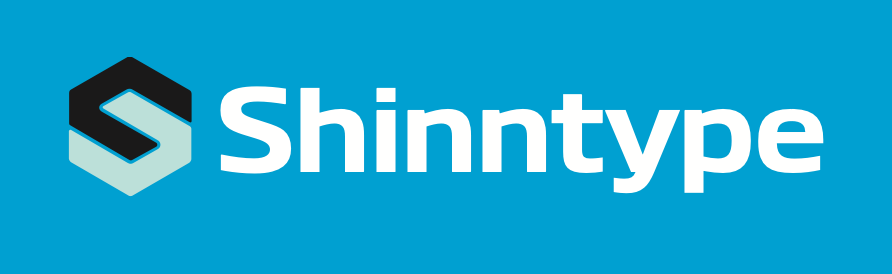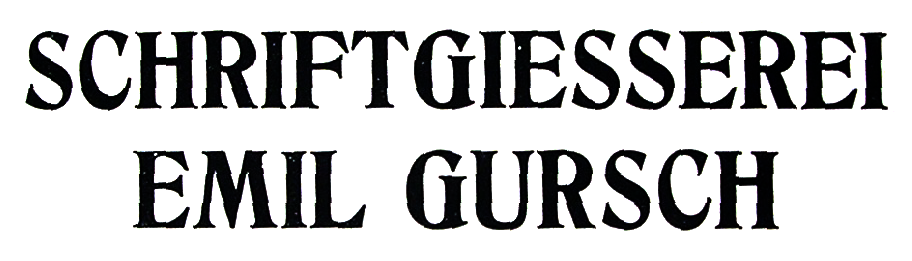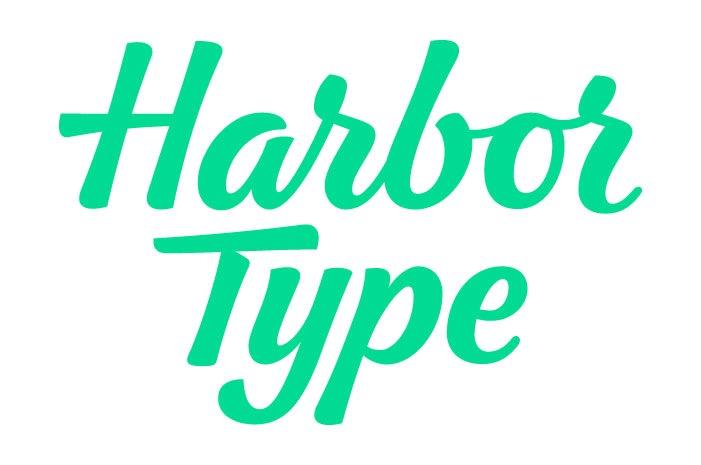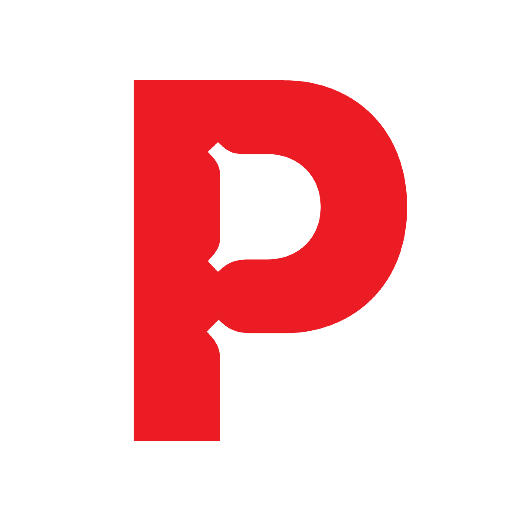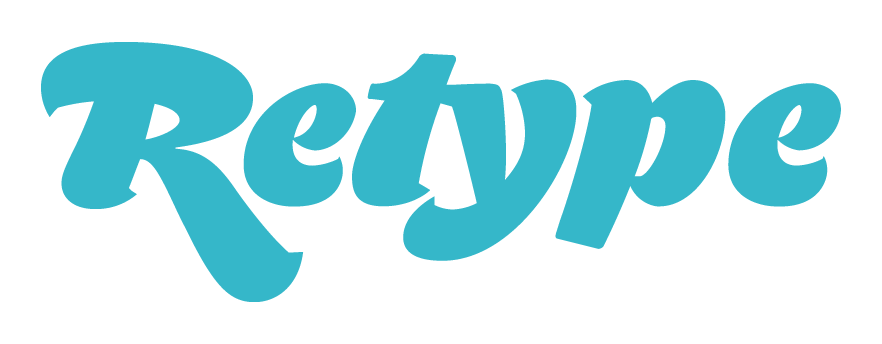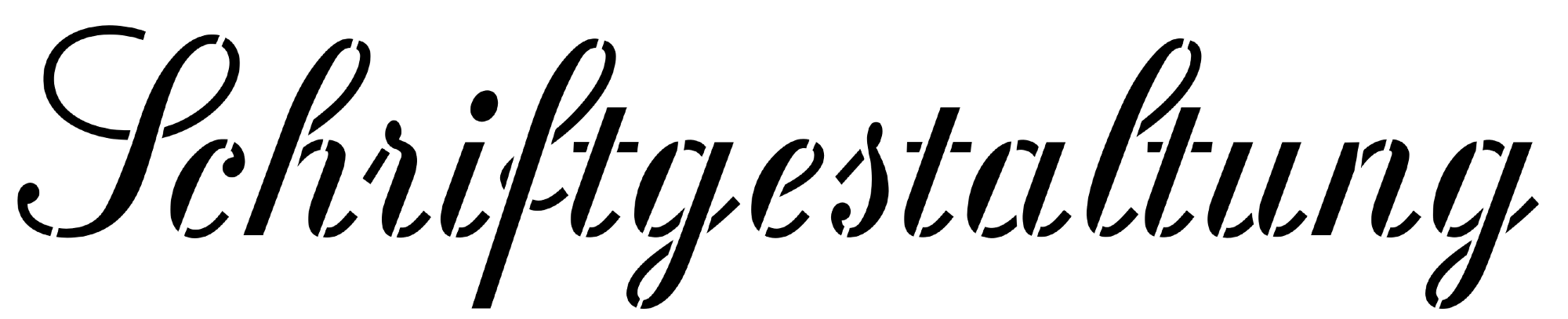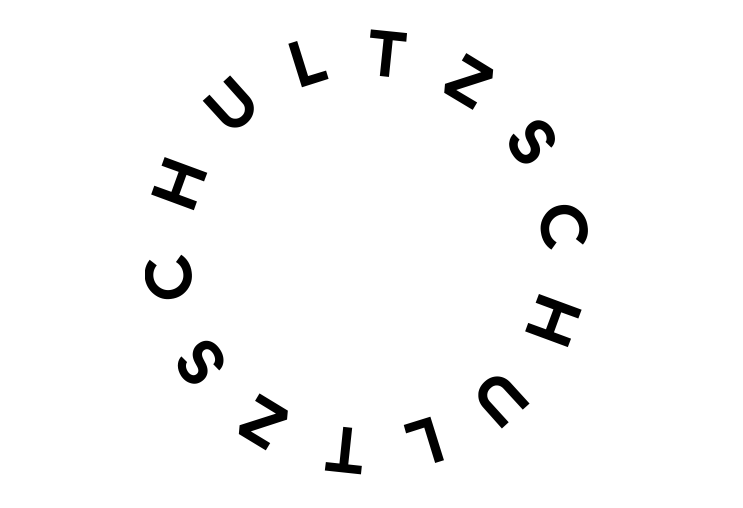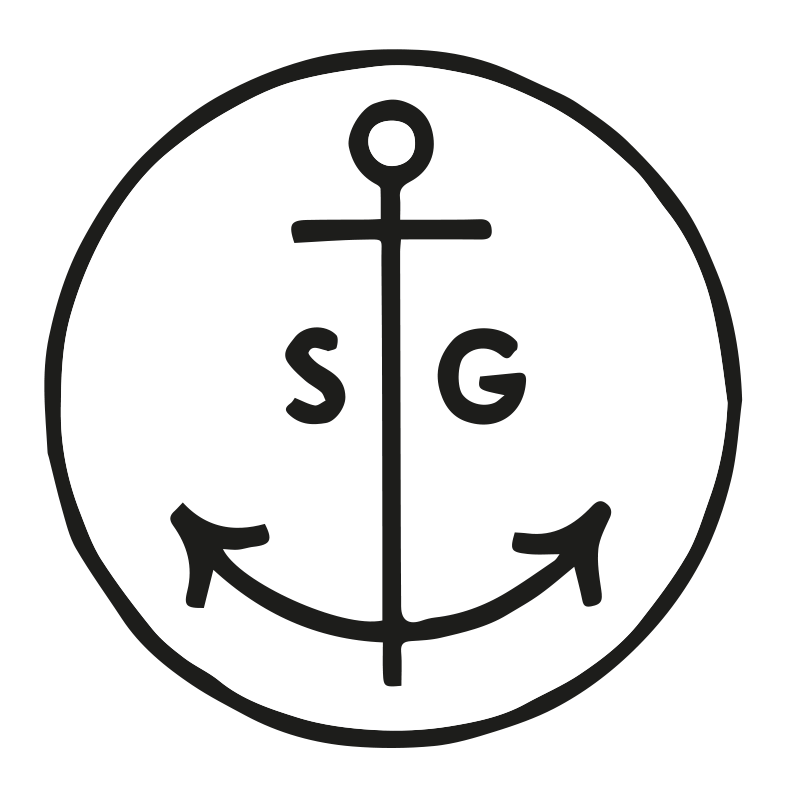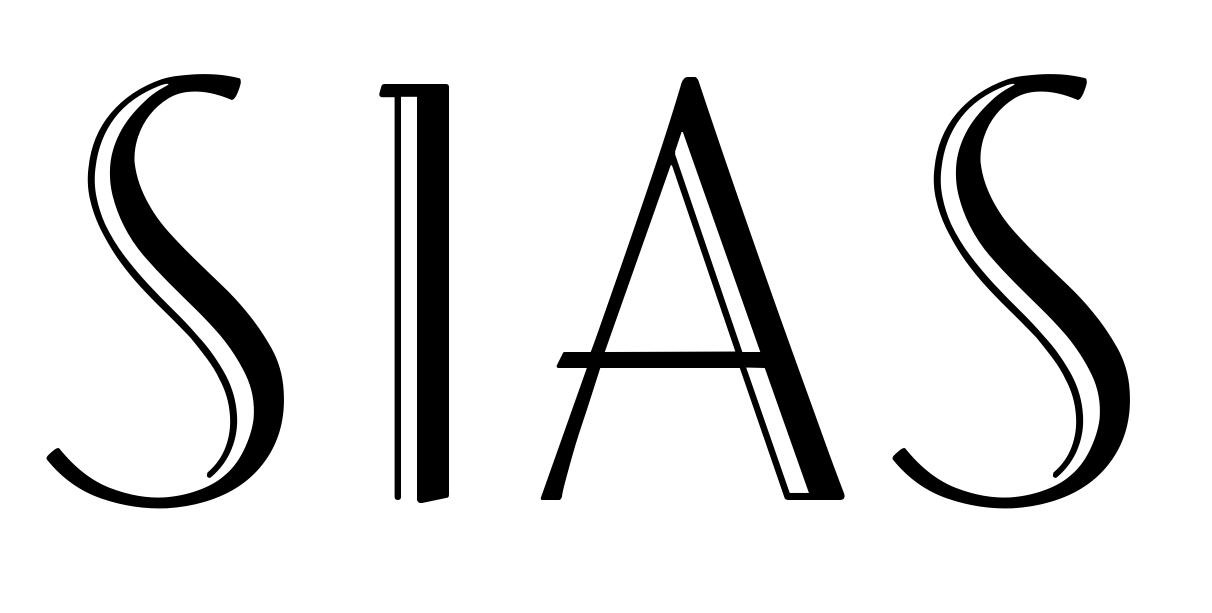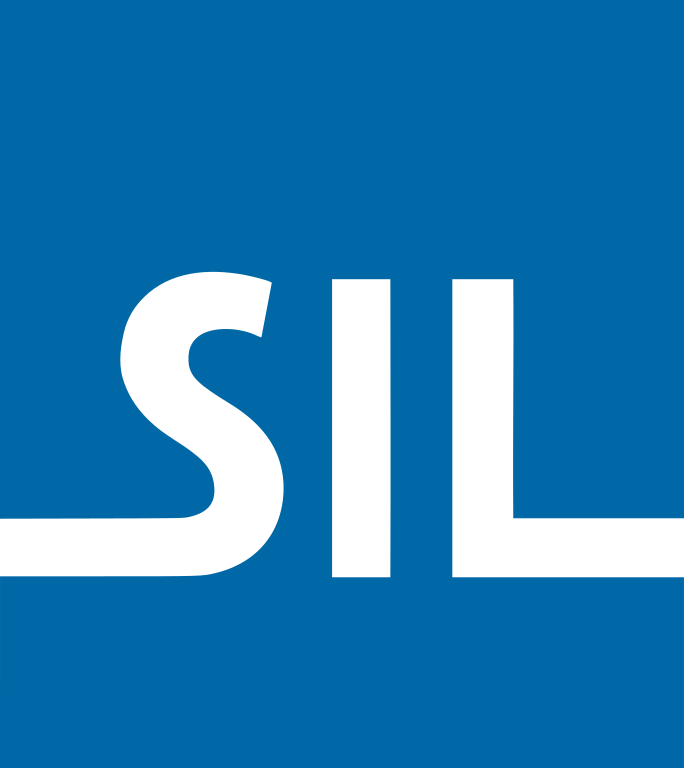
Schriftanbieter
Schriftanbieter, die im Schriften-Wiki verzeichnete Schriften herausgegeben haben
Okay Type ist das Schriftenlabel des Designers Jackson Cavanaugh.
Okaycat ist ein kananisches Label mit Schriften von Natsuko Hayashida und Luke William Turvey.
Omnibus-Type ist ein Schriftenlabel dessen Designer vornehmlich aus Argentinien und Mexiko stammen. Das Label produziert vor allem kostenlose Webfonts.
Optimo ist eine schweizerische Type Foundry mit Sitz in Genf.
Ourtype war ein Schriftenlabel von Fred Smeijers, Corina Cotorobai, Rudy Geerarts und Martine Leloup. Das Label bestand zwischen 2002 und 2018.
Ein englischer Schriftanbieter, der von Mitte des 19. bis in the 2. Hälfte des 20. Jahrhunderts unter verschiedenen Namen (wie Patent Type Foundry, Stevens, Shanks & Sons Ltd ) agierte.
P22 ist der Name eines in Buffalo (New York) ansässigen Schriftanbieters, der von Richard Kegler und Carima El-Behairy gegründet wurde. P22 hat sich insbesondere der Digitalisierung und Pflege von historischen Schriften verschrieben. Dazu wurden im Laufe der Zeit auch die Anbieter Sherwood Type Collection, Lanston Type Co. und Rimmer Type Foundry übernommen, deren Bibliotheken weiter ausgebaut und digital aufbereitet werden. Das Label ist mittlerweile zu The Type Founders LLC gewechsel
PampaType ist ein argentinisches Schriften-Label, das 2001 von Alejandro Lo Celso ins Leben gerufen wurde.
Parachute ist ein griechisches Schriftenlabel, das 2001 von Panos Vassiliou gegründet wurde.
ParaType Inc. wurde 1998 als Nachfolger der Schriftabteilung von ParaGraph Intl. gegründet. Das Unternehmen ist insbesondere für seine Arbeit für den Markt der kyrillischen Schriften bekannt. Das Unternehmen hat Geschäftssitze in Moskau sowie in Saratoga (Kalifornien).
Parkinson Type Design ist das Schriftenlabel von Jim Parkinson.
phospho ist der Name des Designerstudius und der Type Foundry des österreichischen Designers Roland Hörmann.
PintassilgoPrints ist ein brasilianische Designstudio und eine Foundry, die von Ricardo Marcin und Erica Jung betrieben wird.
Pixilate ist ein schwedisches Schriftenlabel, das von Kemie Guaida betrieben wird. Das Label hat sich auf Handschriften spezialisiert.
Ein Designstudio in Istanbul, Türkei.
Playtype ist ein dänisches Schriftenlabel, das von der Agentur e-Types ins Leben gerufen wurde.
Um seinen zunehmenden Hunger nach neuen Schriften zu stillen, gründete Neil Summerour im Jahr 2000 das Schriftlabel Positype. Über 60 Schriftfamilien wurden darüber bereits veröffentlicht. Außerdem entstanden zahlreiche Exklusiv-Schriften für große und kleine Auftraggeber.
Posterizer KG ist das Schriftenlabel des serbischen Designers Lazar Dimitrijević.
Das Schriftenlabel von Ingo Preuß.
Primetype ist das Schriftenlabel von Ole Schäfer aus Berlin.
Process Type Foundry wurde 2002 von Eric Olson gegründet. Neben seiner Arbeit als Grafikdesigner fand er zunehmend mehr Spaß an der Gestaltung von Schriften und eröffnete kurzerhand ein eigenes Label, das in der Folge mit Schriften wie der Klavika sehr erfolgreich wurde.
Production Type ist ein in Paris ansässiger Schriftanbieter, der von Jean-Baptiste Levée geführt wird. Zu den beteiligten Schriftgestaltern gehören Yoann Minet, Sandra Carrera, Yohanna My Nguyen, Emmanuel Besse, Mathieu Réguer und Loic Sander.
Profonts (Eigenschreibung profonts) ist ein Hamburger Schriftenlabel, das von Peter Rosenfeld und Jürgen Willrodt betrieben wird. Schwerpunkt der Bibliothek bilden Neuinterpretation von Schreibschriften und Displayfonts.
Re-Type ist ein Schriftenlabel des argentinischen Designer Ramiro Espinoza.
Resistenza ist ein Designstudio und eine Foundry betrieben von Giuseppe Salerno und Paco González.
Revolver Type Foundry ist das Schriftenlabel des Type Designers Lukas Schneider. Lukas Schneider absolvierte den Master-Studiengang Type and Media an der Königlichen Akademie für Bildende Künste in den Haag, Niederlande sowie den Expert Class Type Design Kurs am Plantin Institute of Typography, in Antwerpen, Belgien.
RMU Typedesign ist das Schriftenlabel des deutschen Schriftgestalters Ralph M. Unger.
Rosetta ist eine Schriftenlabel betrieben von David Březina. Der Anbieter hat sich inbesondere auf den Bereich der nichtlateinischen Schriften spezialisiert. Arabisch, Griechisch, Kyrillisch, slawische Sprachen, und viele asiatische Sprachen werden von den Rosetta-Schriften unterstützt.
Sportsfonts ist ein Schriftenlabel von Christoph Koeberlin, dass sich auf die Entwicklung von Schriften für den Bereich Sport spezialisiert hat.
Stephenson Blake & Co war eine britische Schriftgießerei aus Sheffield, die vom 19. Jahrhundert bis in die 1990-er Jahre aktiv war. Sie gilt als die letzte aktive britische Schriftgießerei. Die Materialen der Gießerei befinden sich heute im Type Museum, London.